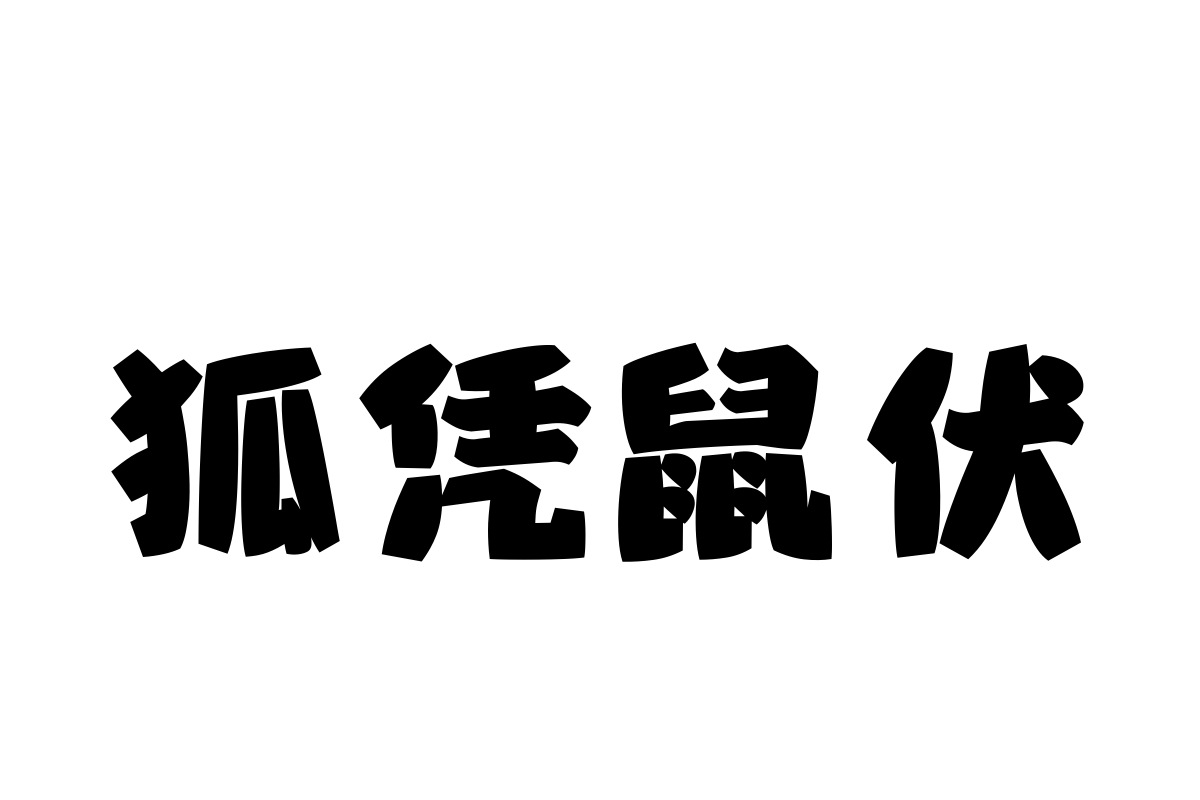
汉仪永字陨石简字体是一款具有中国风的无衬线体,由汉仪公司设计。这款字体以其简洁、现代的设计而受到广泛欢迎,适用于各种印刷和数字媒体。永字陨石简字体的笔画流畅,结构紧凑,给人一种清晰、易读的感觉。同时,它的字形独特,既有传统书法的韵味,又不失现代感。这款字体适用于标题、正文、广告等场景,可以很好地传达出品牌或产品的独特风格。